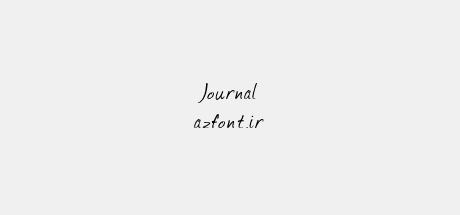
Journal
فونت زیبای رایگان Journal
قلم زیبای Journal از سری قلم های بسیار زیبا برای تایپوگرافی و لوگو تایپ می باشد.این قلم در وزن Regular و توسط High-Logic - Erwin Denissen 1999 طراحی و منتشر شده است.